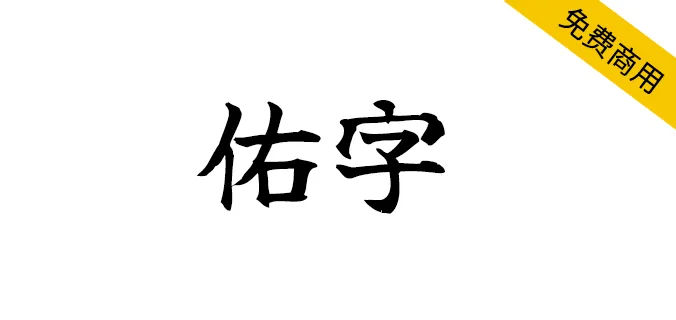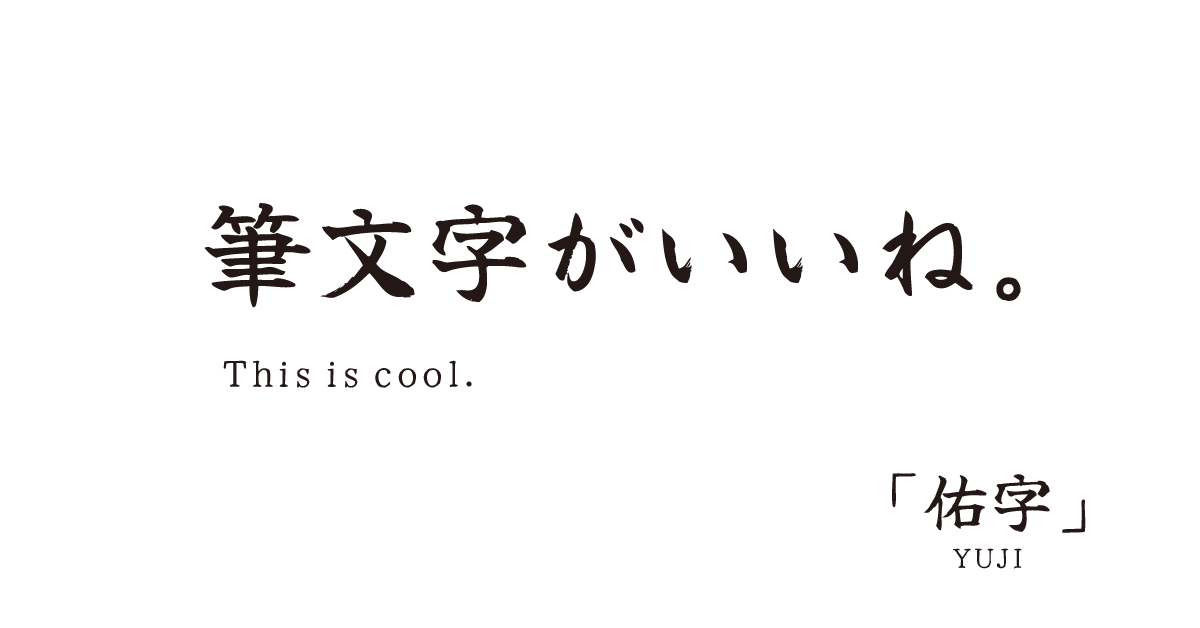
“Yuji”是一系列字體,書法家Yuji Kataoka所寫的原始文字都是用字體印刷的。有3種不同類型的假名和2種不同類型的變體假名字體。
Yuji “Syuku” (佑字【肅】)
它既有傳統和尊嚴,又平易近人。這種設計能被大眾廣泛接受。漢字和一些符號與佑字【舞】和佑字【樸】相同。
Yuji “Mai” (佑字【舞】)
它表達了一種自由、奔放、情感的美。拉丁字母是為了匹配假名筆劃而寫的
Yuji “Boku” (佑字【樸】)
這是一個新的和愉快的設計。它既簡單又溫暖。
Yuji “Akari” (佑字【燈】)
Yuji “Akebono” (佑字【曙】)
現在的平假名是在1900年被規定的。其餘的字符,沒有被選為平假名,被稱為Hentai假名。Hentai假名有幾種類型,Akari和Akebono是其中的兩種。片假名不包括在Hentai假名中。拉丁字母表只設計成大寫字母。小寫字母是大寫的。